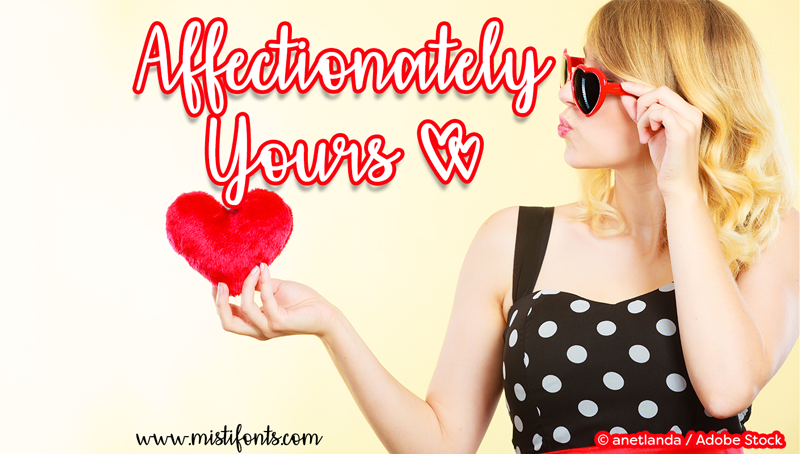
A fonte “Affectionately Yours” é uma escolha perfeita para quem procura um estilo charmoso e elegante que flui facilmente nas suas criações digitais. Ideal tanto para personal use quanto non-profit, a Misti’s Fonts propõe esta fonte como uma ferramenta de criatividade sem custos. Embora gratuita para uso pessoal e não-comercial, é importante ressaltar que qualquer rendimento obtido através do seu uso deve ser suportado com um licenciamento. Esta fonte oferece um tom aconchegante e suave, perfeito para criar texturas em design gráfico ou até mesmo em criações digitais. Com certeza, “Affectionately Yours” será uma excelente escolha para aqueles que buscam expressar afeto de forma elegante e única através do texto. Compreendendo as regras impostas pela fonte, você pode usar esta fonte com prazer em seus projetos sem preocupação. Ao trabalhar com esta fonte, você estará adquirindo uma ferramenta versátil que não só simplifica o processo de criação mas também oferece um toque personalizado e especial aos seus projetos.